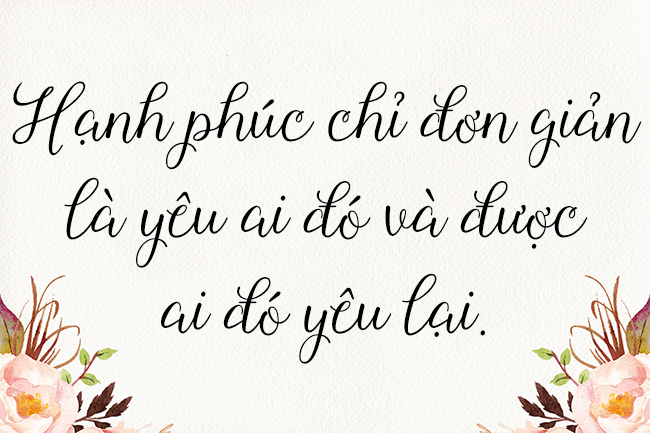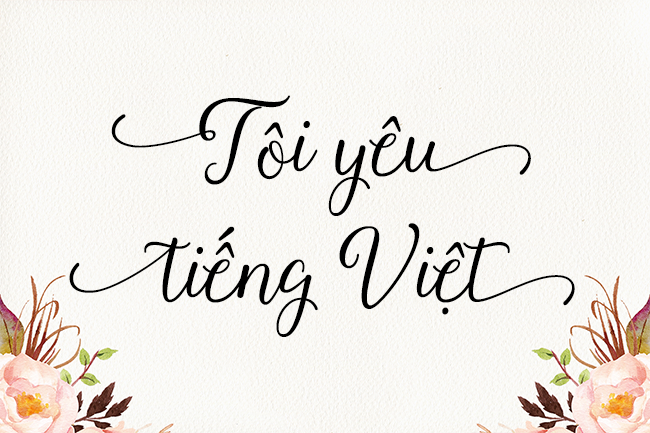
Roselina Script là một font thư pháp đương đại mang hơi hướng cổ điển, phong cách calligraphy với đường baseline uyển chuyển và nét thanh lịch. Font có thể sử dụng cho nhiều mục đích khác nhau như tiêu đề, chữ ký, logo, thiệp cưới, áo thun, giấy tiêu đề, biển hiệu, nhãn mác, ấn phẩm tin tức, poster, huy hiệu, v.v. Roselina Script sở hữu hơn 417 glyph và 183 ký tự thay thế, bao gồm ký tự đầu và cuối, alternates, ligatures cùng khả năng hỗ trợ đa ngôn ngữ.
Nhà thiết kế: Seniors Studio